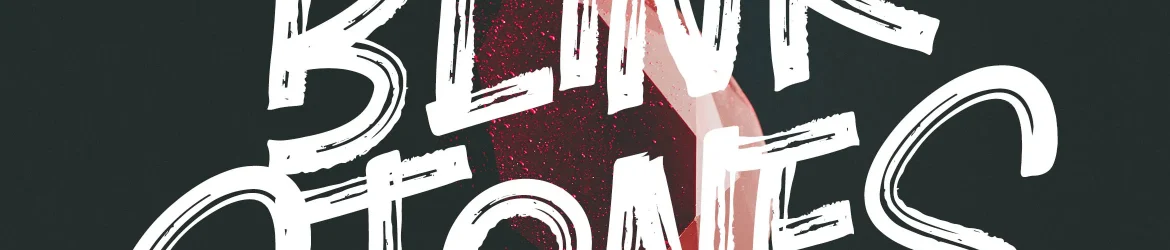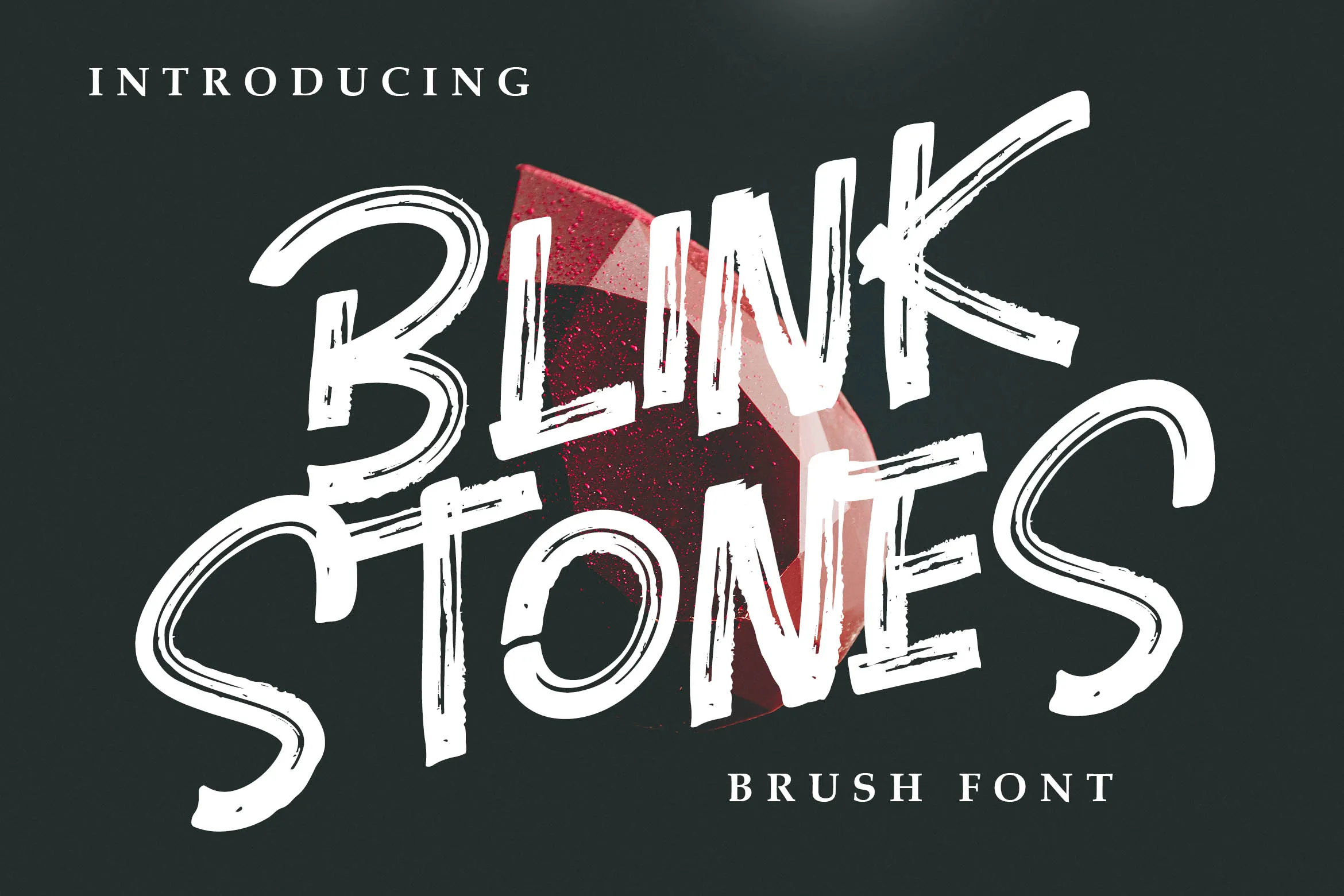
Blink Stones Brush Font – Fonte Grátis
Blink Stones Brush Font
Estou aqui uma nova fonte de traço brush, chamada Blink Stones Font, criada pelo designer Hamilton. Este é um novo design que traz frescura para a família de fonts de script. Ideal tanto para branding como para decorar qualquer projeto, esta font oferece flexibilidade para criar desde logotipos até belas molduras para sua casa. Ou simplesmente use-a em pequenos negócios, capas de livros, materiais de escritório, marketing, blogs e revistas. Com o Blink Stones Font, você pode escolher se deseja dar uma cara moderna a seu negócio ou adicionar um toque único aos seus projetos de design gráfico. Seja em sua marca online, no conteúdo do seu blog ou até mesmo nas capas dos seus livros, esta font será uma excelente opção para ilustrar seus ideais criativos. Não perca tempo e baixe já a Blink Stones Font para começar a explorar todos os usos possíveis desta nova descoberta de Hamilton.